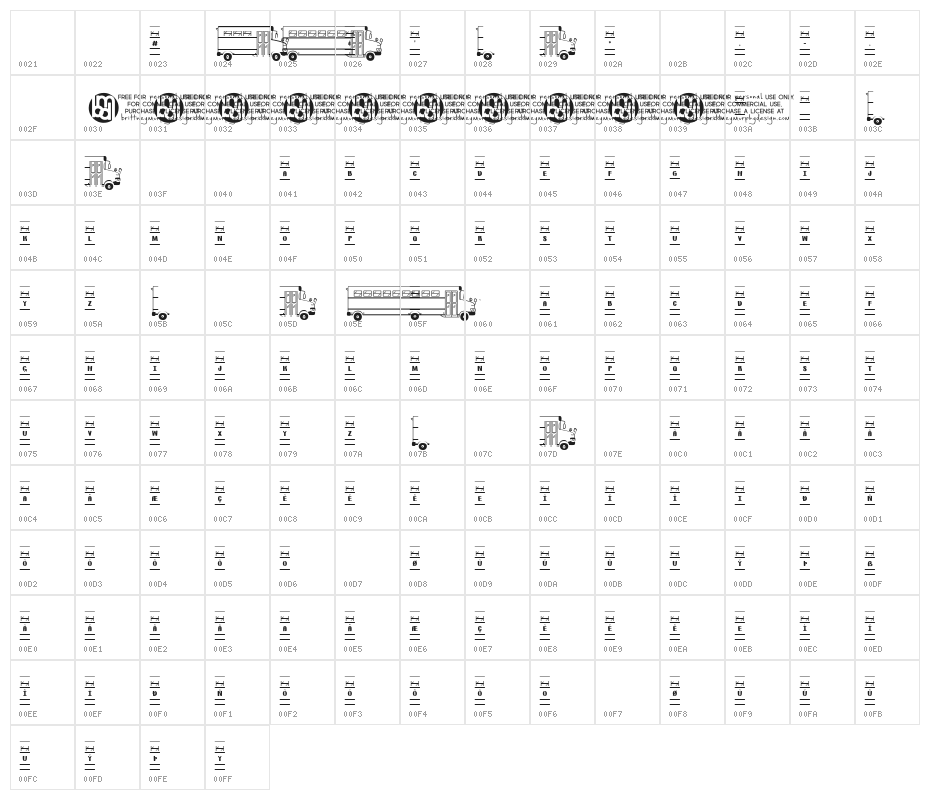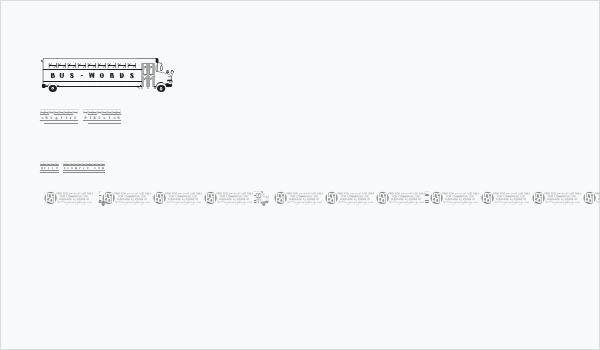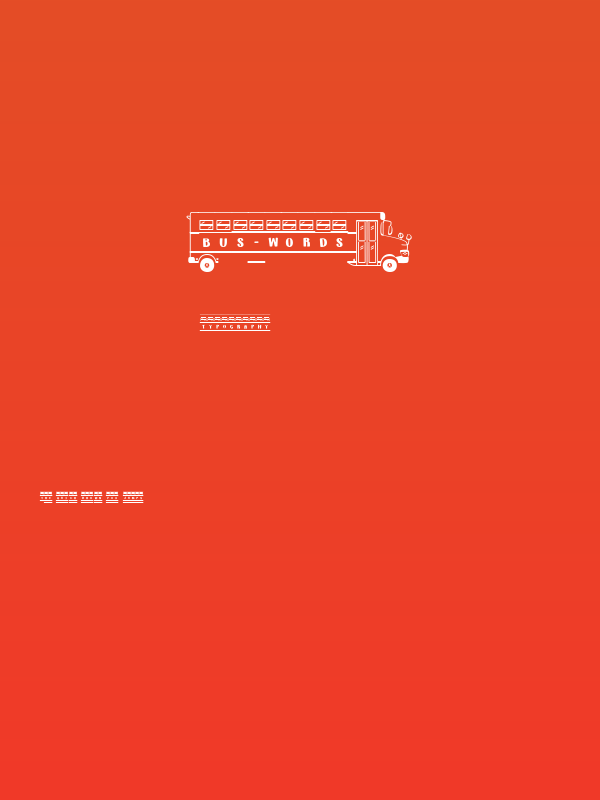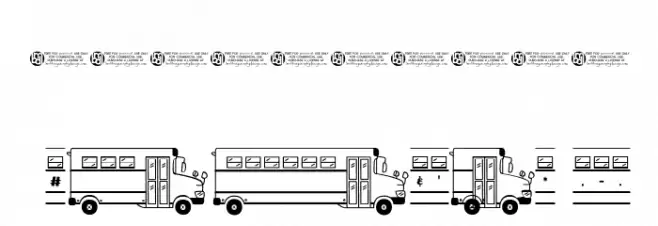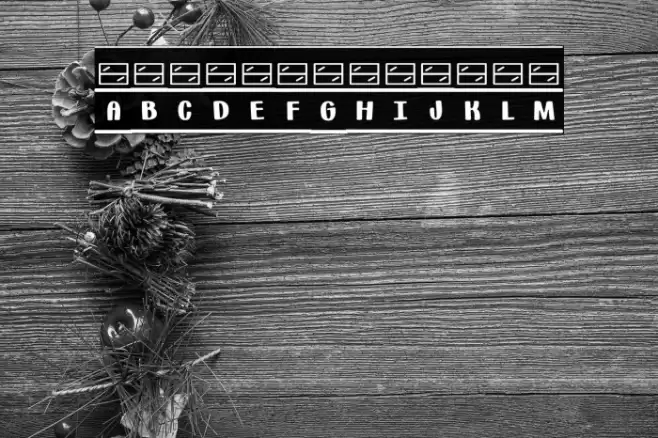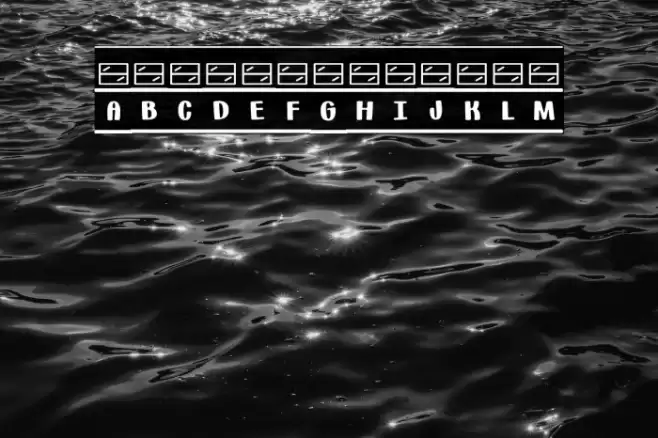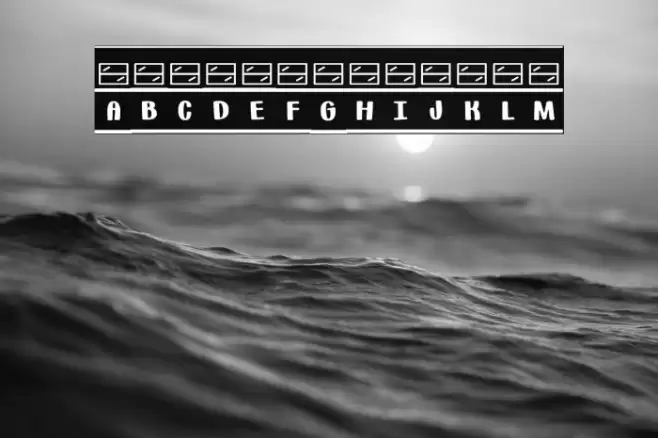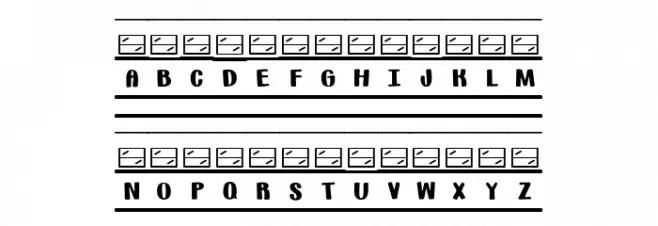
(Bus-words) Font
| Stil general | Playful, Thematic, Decorative |
| Proiecte propuse | Perfect for school event posters, children's book covers, educational materials, and playful branding. |